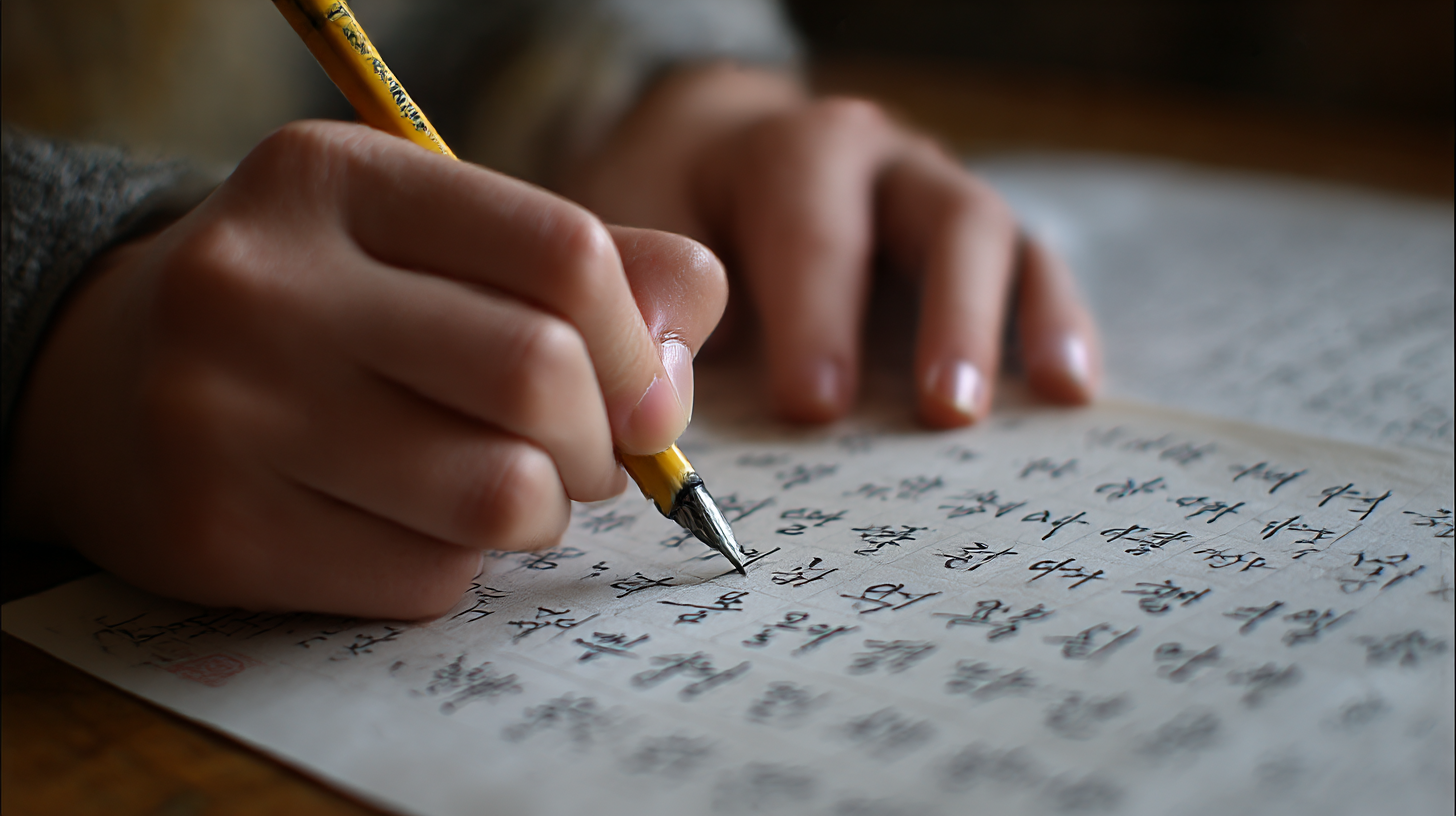
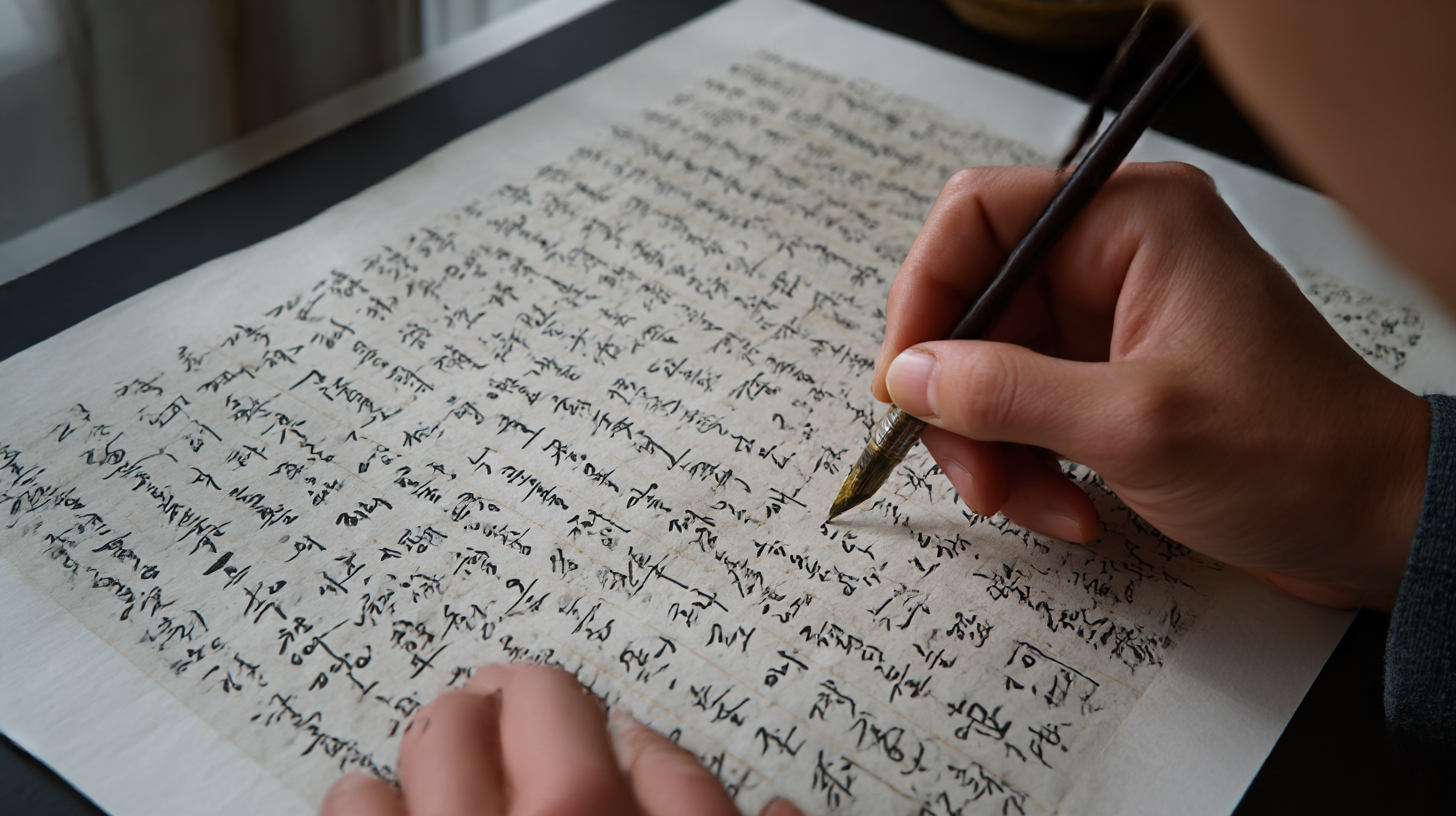
회사에서 인정받는 바른글씨 작성 비법 직장에서는 외모보다 글씨가 먼저 인상을 남길 때가 많아요. 회의자료, 메모, 업무 노트에서 글씨는 곧 나를 대표하는 얼굴이 되기도 해요. 글씨 하나 바뀌었을 뿐인데 “성실하다”, “정리정돈 잘한다”는 칭찬을 들은 분들도 정말 많답니다.
그렇다면 어떻게 하면 회사에서 칭찬받는 ‘바른 글씨’를 쓸 수 있을까요? 특별한 재능이 없어도 누구나 실천 가능한 방법들을 지금부터 알아볼게요. 내가 생각했을 때 글씨는 습관이에요. 매일 조금씩 바르게 쓰려고 노력하면 얼마든지 멋진 글씨체가 내 것이 된답니다! 😊
✏ 글씨체가 주는 첫인상의 힘
직장에서 글씨는 당신의 이미지를 형성하는 데 큰 역할을 해요. 예쁘게 정돈된 글씨는 신뢰감, 성실함, 집중력 있는 사람으로 보이게 만들죠. 반면, 지저분한 글씨는 일의 완성도까지 낮춰 보일 수 있어요. 상사나 동료가 여러분의 업무 메모나 회의 노트를 보는 순간, 글씨로 인상을 받는 경우가 많답니다.
특히 보고서나 회의록을 직접 손글씨로 작성할 경우, 글씨가 가지는 무게감은 더 커져요. 아무리 좋은 내용을 담고 있어도 읽기 어려운 글씨라면 전달력이 떨어지고 신뢰도까지 깎일 수 있죠. 실제로 많은 회사에서는 직원의 글씨체를 평가 기준의 하나로 삼기도 해요.
또한, 깔끔하고 일정한 글씨는 본인의 사고 방식까지 잘 정돈되어 있다는 느낌을 주기 때문에 업무 능력까지 높게 평가받을 수 있어요. 이런 이유로 ‘글씨 하나 잘 써서 승진했다’는 이야기까지 있을 정도예요.
직장인에게 글씨는 단순한 표현 수단이 아니에요. 명함처럼 자신의 이미지를 보여주는 도구예요. 그렇기 때문에 지금부터라도 조금씩 바른 글씨 연습을 시작하면 업무 능력과 함께 이미지까지 동시에 좋아질 수 있어요.✌
📝 글씨체별 인상 비교표
글씨 유형 주는 인상 추천 상황 둥글고 단정한 글씨 부드럽고 친근함 회의 메모, 피드백 획이 굵고 또렷한 글씨 결단력 있고 정확함 보고서, 기획서 기울어진 글씨 창의적이고 감성적 아이디어 회의, 제안서 작고 정돈된 글씨 섬세하고 논리적 업무 노트, 체크리스트 각 글씨체는 상황에 따라 더 효과적으로 쓰일 수 있어요. 따라서 자신만의 스타일을 만드는 것도 중요하지만, 상황에 맞게 글씨 분위기를 조절하는 능력도 실무에선 매우 유용하답니다!
📐 바른글씨를 위한 기본 원칙
바른글씨를 쓰기 위해서는 단순히 예쁘게만 쓰려고 하지 말고, 기본 원칙을 지키는 것이 훨씬 중요해요. 기본적인 획과 자형, 자간, 행간만 잘 맞춰줘도 깔끔한 인상을 줄 수 있답니다. 글씨 연습을 시작할 때 가장 먼저 해야 할 건 글자의 구조를 이해하는 거예요.
예를 들어, 모든 자음과 모음은 일정한 기준선을 따라 쓰는 것이 중요해요. 초성은 왼쪽, 중성은 가운데, 종성은 아래쪽에 정렬하는 원칙만 지켜도 전체적으로 안정감 있는 글씨가 돼요. 한 글자 안에서 중심축을 일정하게 유지하면 전체 문장이 흐트러지지 않아요.
자간은 너무 좁지도 넓지도 않게 일정하게 유지해야 해요. 너무 좁으면 답답해 보이고, 너무 넓으면 흐트러진 느낌이 나요. 한글은 정사각형 틀 안에 글자를 맞춰 쓰는 것이 기본이라서, 가상의 정사각형 안에 각 글자가 정확히 들어간다는 느낌으로 연습해 보세요.
글씨를 바르게 쓰려면 속도 조절도 중요해요. 급하게 쓰면 글자의 균형이 무너지고 획이 휘어지기 쉬워요. 일정한 속도로 천천히 써 내려가면 손의 움직임도 안정되고 글씨가 훨씬 고르게 보이게 돼요. 급한 메모를 할 때도 의식적으로 균형을 생각해보면 훨씬 나아져요.
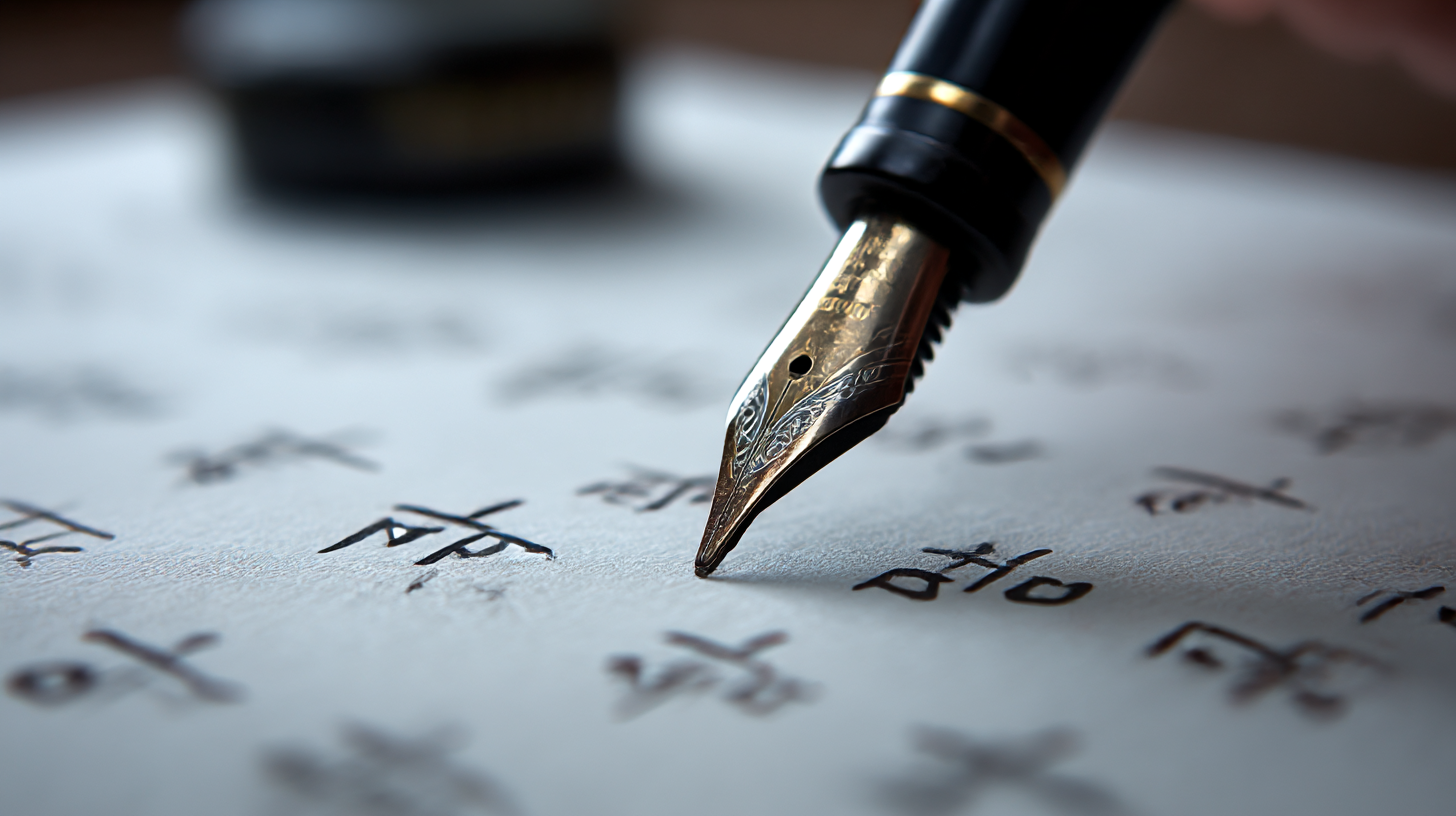
바른글씨를 위한 기본 원칙 📏 바른글씨 원칙 요약표
항목 설명 주의사항 자형 정렬 가상의 정사각형 안에 글자 균형 맞추기 중심선 무너지지 않도록 자간 유지 글자 간 일정한 간격 유지 너무 붙거나 멀어지지 않게 획의 균형 가로·세로 획의 두께와 길이 일정하게 한 쪽으로 쏠리지 않게 속도 조절 급하게 쓰지 말고 일정한 리듬 유지 빨리 쓰면 글씨가 휘어짐 기본을 지키는 것이 곧 실력이에요. 특별한 장식 없이도 바르고 단정한 글씨는 직장 내에서 가장 큰 무기가 될 수 있답니다. 기본기부터 다시 다져보면, 누구든 멋진 글씨체를 가질 수 있어요! 💪
🖋 글씨 연습 루틴 만들기
바른 글씨를 위해선 규칙적인 연습이 가장 중요해요. 하루 10분만 투자해도 한 달 후에는 놀라운 변화를 느낄 수 있어요. 꾸준함은 실력을 만들고, 실력은 곧 자신감이 되죠. 글씨 연습도 마찬가지예요. 처음부터 멋진 글씨를 쓸 수는 없지만, 올바른 루틴을 통해 분명히 발전할 수 있어요.
가장 먼저 해야 할 것은 ‘기본 획 연습’이에요. 세로획, 가로획, 점, 꺾임 등을 규칙적으로 반복하면서 손에 익히는 것이 핵심이에요. 한글은 특히 ‘ㅅ’, ‘ㅈ’, ‘ㅂ’처럼 꺾임이 많은 글자가 많기 때문에 획 연습은 필수예요. 기본 획이 안정되면 자연스럽게 자형도 안정돼요.
그다음에는 자주 쓰는 단어들을 중심으로 연습해보세요. “보고서”, “기획안”, “회의록” 같은 직장에서 자주 쓰는 단어들을 쓰는 연습을 하면 실전에서도 당황하지 않고 또박또박 쓸 수 있어요. 단어가 익숙해질수록 손도 편해지고, 글씨체도 자연스러워져요.
마지막으로는 문장 단위로 연습하는 걸 추천해요. 짧은 문장을 적어보면서 자간과 행간, 글줄 정렬까지 익혀보세요. 연습 문장으로는 책 속의 문장이나 명언 등을 활용하면 의미도 있고 흥미도 생기죠. 매일 한 문장이라도 쓰는 습관이 실력을 만들어줘요!
🗓 추천 글씨 연습 루틴표
요일 연습 내용 소요 시간 월요일 기본 획 연습 (세로/가로/점/꺾기) 10분 화요일 자형 중심 연습 (가상의 정사각형) 15분 수요일 실무 단어 쓰기 (회의, 업무명 등) 10분 목요일 속도 조절 및 일정한 필기 연습 10분 금요일 문장 연습 (명언/기사 등 필사) 15분 매일 정해진 시간에 같은 루틴을 반복하면 뇌가 자연스럽게 ‘글씨 쓰는 시간’으로 인식하게 돼요. 습관이 되면 손도 마음도 편안해져서 더 좋은 글씨를 쓸 수 있게 되죠. 누구나 멋진 글씨를 가질 수 있어요. 지금 당장 오늘부터 시작해봐요! 💫
🖊 도구 선택도 중요해요
글씨 연습에서 도구는 생각보다 정말 큰 영향을 줘요. 펜 하나 바꿨을 뿐인데 글씨 느낌이 달라지고, 손에 힘도 다르게 들어가거든요. 자신에게 잘 맞는 펜과 노트를 찾는 것은 마치 운동화 고르듯이 신중해야 해요. 손의 압력, 종이의 질감, 펜촉의 흐름까지 모두 글씨체에 영향을 줘요.
먼저 펜은 너무 미끄럽거나 끊기는 느낌이 없도록 부드럽게 써지는 것을 고르는 게 좋아요. 유성볼펜보다는 젤펜이나 수성펜이 글씨 연습용으로는 더 좋다는 평이 많아요. 특히 0.38mm~0.5mm 굵기의 젤펜은 획이 균일하게 나와서 자형을 잡기 쉬워요.
종이는 너무 미끄럽거나 너무 거친 표면은 피하는 게 좋아요. 매끄럽지만 살짝 텍스처가 있는 종이가 글씨 연습에는 적합하답니다. 유선 노트도 좋지만, 글씨체를 정돈하려면 모눈 노트나 10mm 간격의 가이드 노트도 적극 추천해요.
추가로, 바른 자세와 그립도 중요해요. 펜을 너무 꽉 쥐면 손에 피로가 오고 글씨도 흐트러지기 쉬워요. 손가락 끝이 펜촉에서 2cm 정도 떨어지게 잡고, 손목은 힘을 빼는 게 핵심이에요. 올바른 도구와 자세는 글씨 연습의 기초 체력을 길러주는 역할을 해요.💪
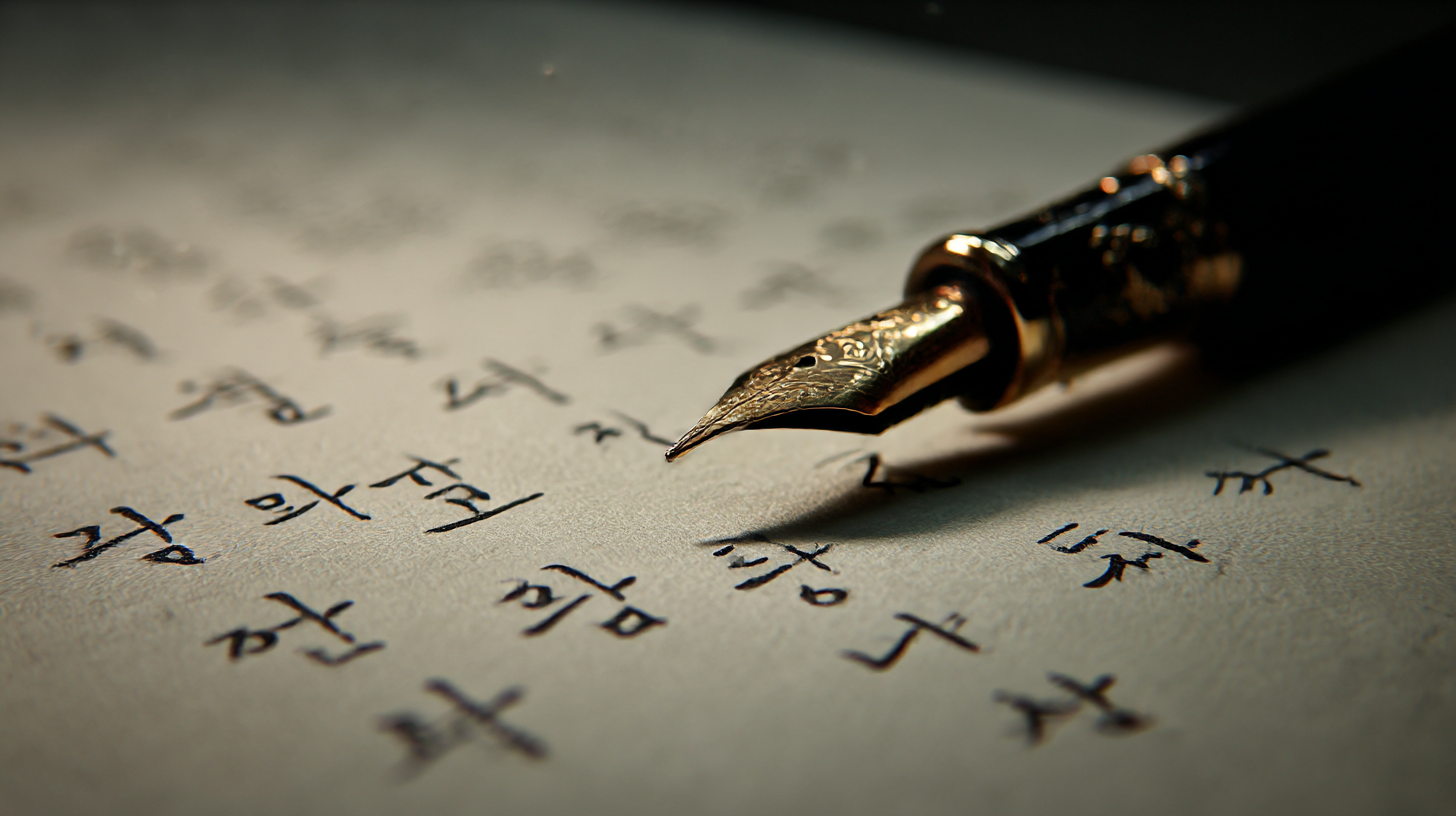
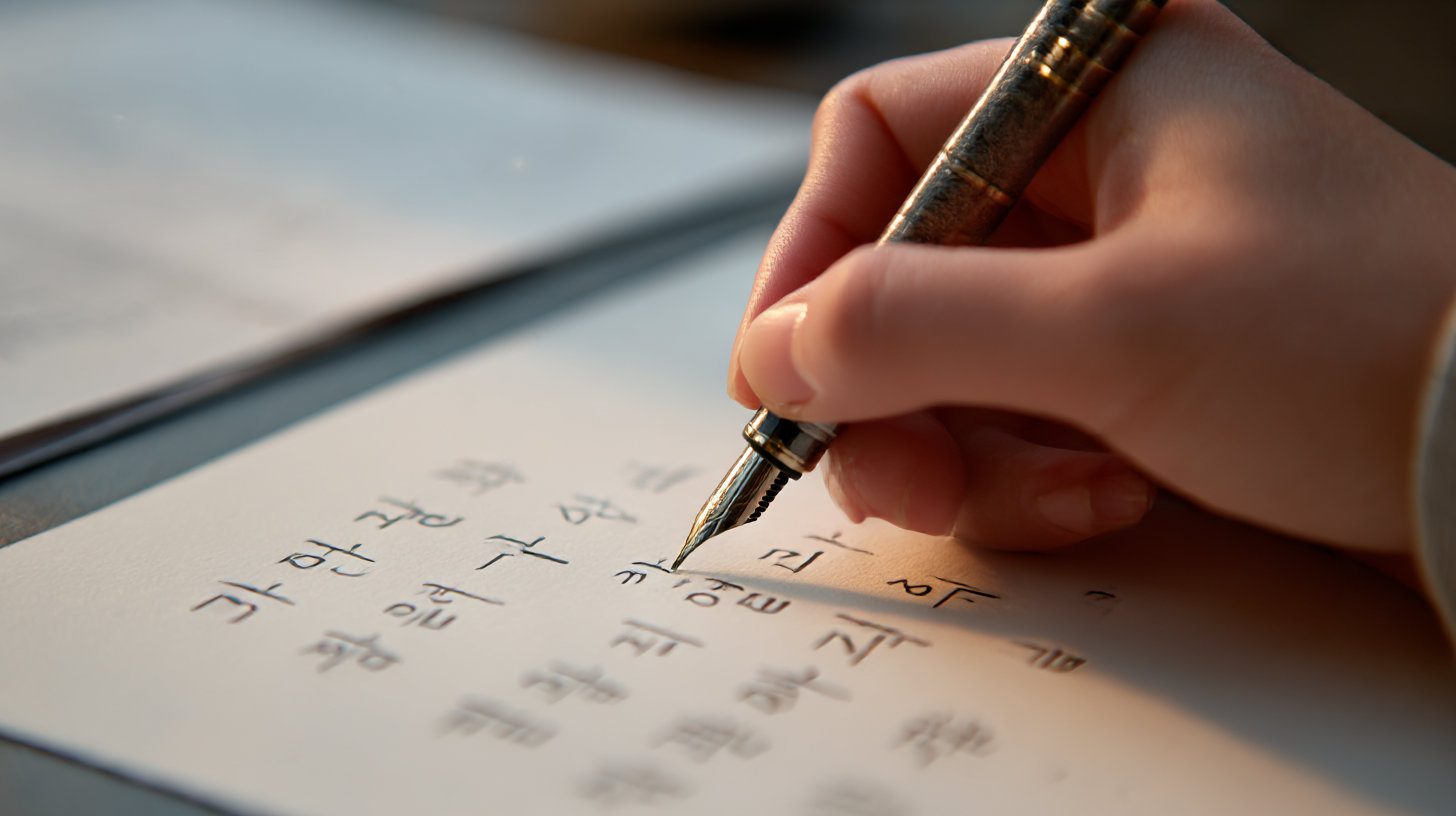
도구 선택도 중요해요 ✍ 추천 필기 도구 비교표
도구 특징 추천 사용자 젤펜 0.38mm 선이 얇고 섬세하게 나옴 초보자, 글자 균형 잡기 용이 수성펜 부드러운 필기감 중간 숙련자, 감성 글씨 연습 만년필 획의 두께 조절 가능 고급 필기체 연습용 모눈 노트 자간·자형 연습에 적합 글씨체 교정 단계에 추천 글씨 연습의 성공은 도구 선택에서 시작돼요. 손에 맞는 펜을 찾고, 내가 좋아하는 노트에 글씨를 써보는 것만으로도 글씨체는 점점 안정돼요. 자신에게 가장 잘 맞는 도구를 찾는 것부터 시작해보세요! 🎯
📄 회사에서 통하는 글씨 습관
회사에서 칭찬받는 글씨는 단순히 예쁘기만 한 게 아니에요. 명확하게 읽히고, 실용적으로 구성돼야 해요. 바로 그런 글씨가 ‘실무형 바른 글씨’랍니다. 이 실무형 글씨를 쓰기 위해선 몇 가지 글쓰기 습관을 갖는 게 정말 중요해요. 습관 하나만 바꿔도 인상이 확 달라진답니다.
먼저, 문서나 메모를 작성할 때 일정한 글자 크기를 유지하는 것이 좋아요. 글씨 크기가 들쭉날쭉하면 가독성이 떨어지고 상대방이 읽기 불편하거든요. 특히 회의 중 작성하는 노트나 피드백 메모일수록 글자 크기를 신경 써야 해요.
또한, 중요한 단어나 항목은 여백을 활용해 강조하면 좋아요. 형광펜이나 밑줄을 사용하는 대신, 글씨만으로 포인트를 주고 싶다면 글자를 약간 굵게 쓰거나, 정자체를 사용하는 게 효과적이에요. 형식적인 표현보단 실용적인 글씨 배치가 업무에서는 훨씬 신뢰를 얻어요.
그리고 메모나 회의록 작성 시, 줄을 맞추는 습관도 매우 중요해요. 줄 간격과 문단 정렬이 깔끔하면 보고하는 자료로도 손색이 없거든요. 메모장에 글을 작성할 때도 항상 좌우 여백을 신경 쓰면서 쓰는 습관을 들이면 자연스럽게 정돈된 인상을 줄 수 있어요.👌
📘 실무형 글씨 습관 비교표
좋은 습관 효과 적용 상황 글자 크기 일정하게 유지 가독성 향상, 안정된 인상 회의 노트, 메모장 여백 활용한 강조 내용 전달력 향상 업무 피드백, 요약 정리 줄 맞춤 & 정렬 전문적이고 깔끔한 인상 보고서, 회의록 줄 간격 일정 유지 읽는 이의 집중력 증가 수첩, 필기 노트 직장에서는 ‘보기 좋은 글씨’가 아니라 ‘읽기 쉬운 글씨’가 칭찬받는 법이에요. 실무에서 바로 사용할 수 있는 글씨 습관을 꾸준히 연습해두면, 어느 순간 동료들이 “글씨 너무 잘 쓰시네요”라고 말해줄 거예요! 😄
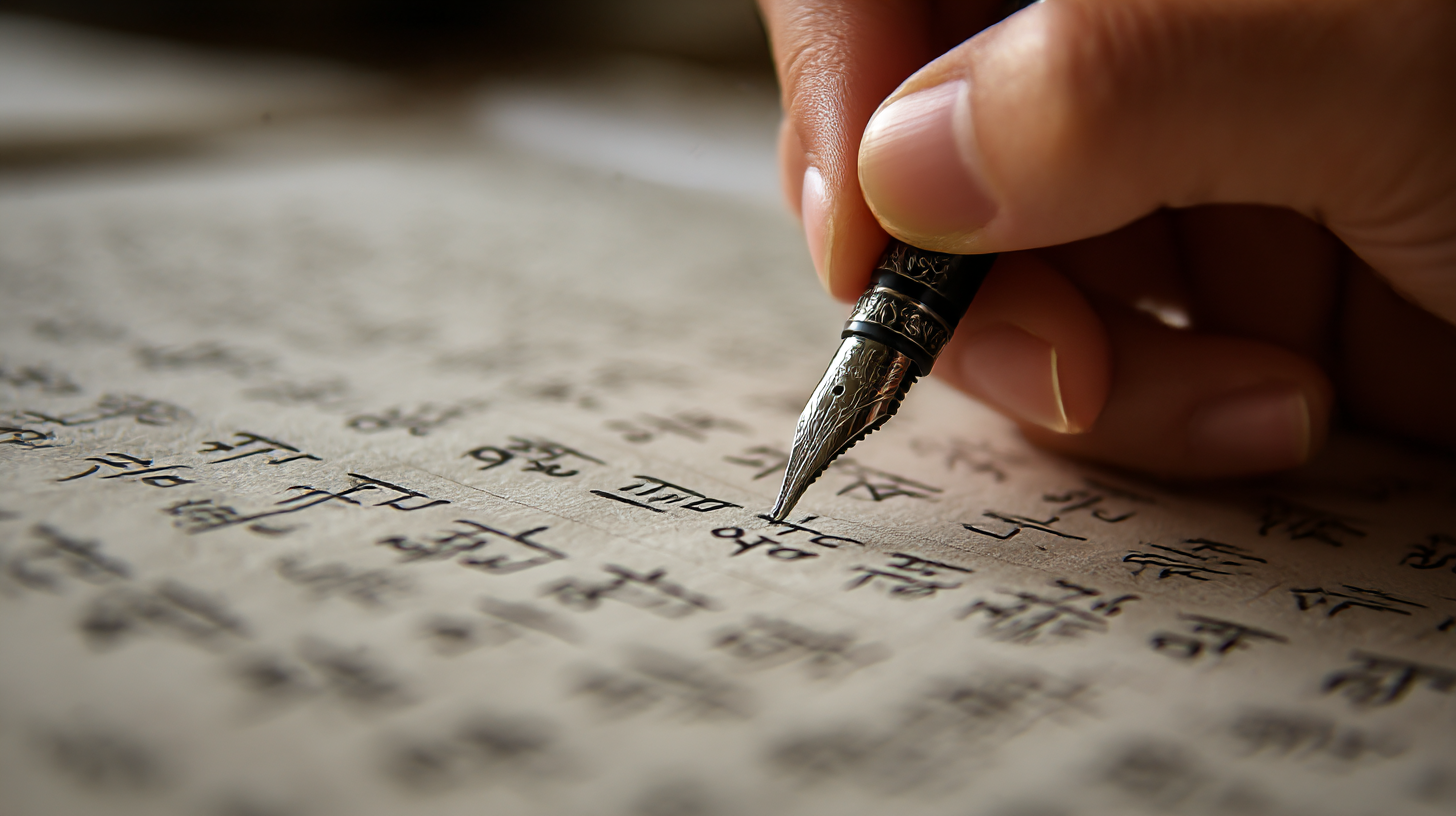
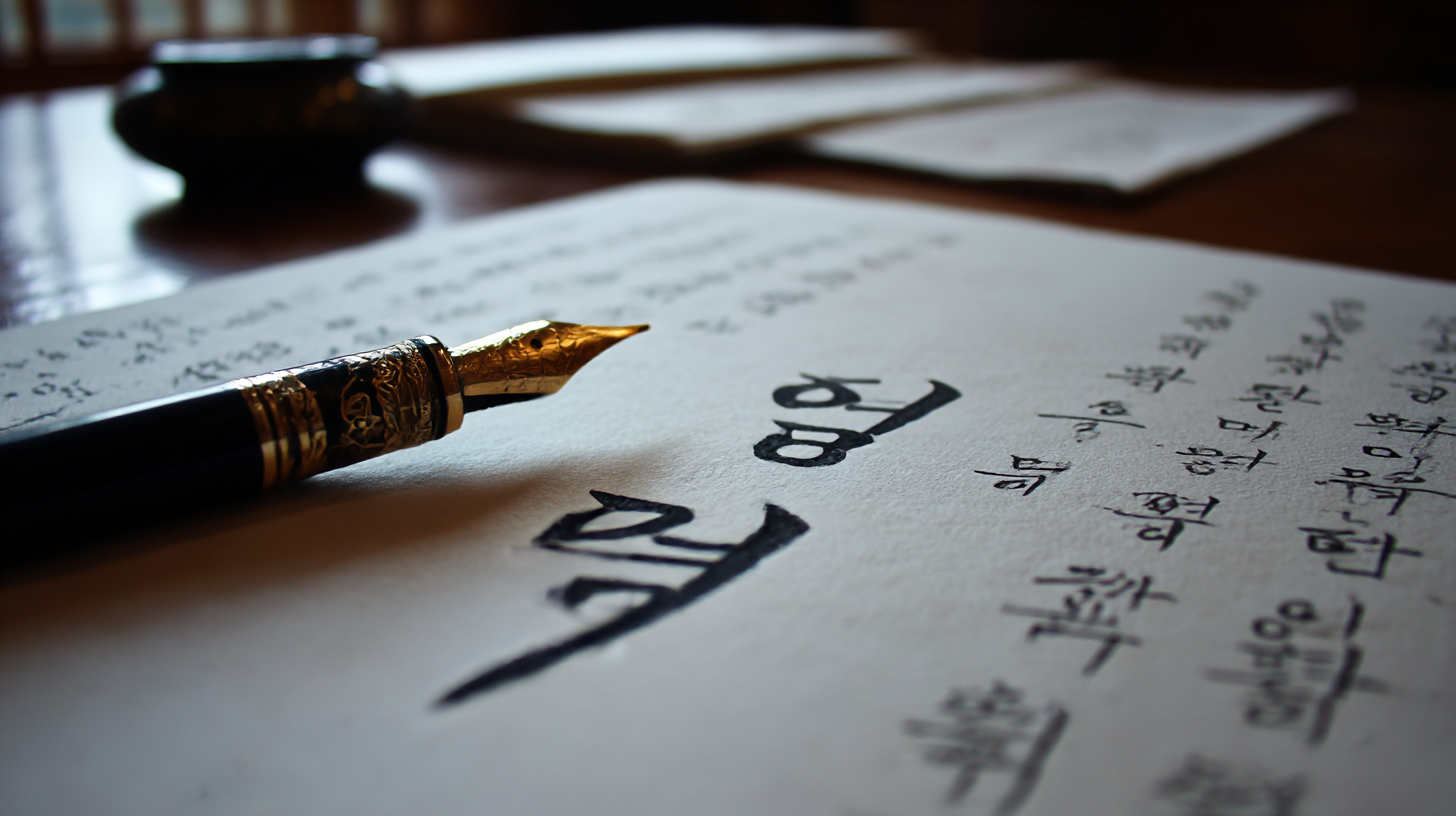
회사에서 통하는 글씨 습관 🧠 글씨체가 성격까지 보여줄까?
우리가 무심코 쓰는 글씨에도 성격과 기질이 드러난다고 해요. 실제로 심리학에서는 글씨체를 분석해 성향을 파악하는 '그래포로지(graphology)'라는 분야도 존재해요. 물론 과학적인 진단은 아니지만, 글씨에서 느껴지는 분위기나 정돈 상태를 보면 그 사람의 성향을 어느 정도 유추할 수 있어요.
Q4. 펜 추천해줄 수 있나요?
A4. 0.38mm 젤펜(하이테크C, 유니볼 시그노)이나 수성펜(플래티넘 프레피) 추천드려요. 필기감도 좋고 초보자에게도 딱이에요.
Q5. 글씨체 교정을 독학으로 해도 괜찮을까요?
A5. 네! 요즘은 유튜브나 필사노트, 연습장도 많아서 혼자서도 충분히 가능해요. 꾸준한 연습만이 정답이에요.
Q6. 글씨체 하나로 성격까지 판단될 수 있나요?
A6. 완전히 판단할 순 없지만, 글씨에서 느껴지는 분위기나 인상은 분명히 성격의 일부를 반영하기도 해요.
Q7. 글씨 연습 시간을 언제 정하는 게 좋을까요?
A7. 아침 출근 전 10분, 점심시간 후 여유시간, 잠들기 전 등이 좋아요. 반복성이 중요해서 하루 한 번이라도 정해두는 게 좋아요.
Q8. 회사에서 글씨 잘 쓰면 진짜로 칭찬을 받을까요?
A8. 네! 특히 상사나 동료가 여러분의 메모나 회의록을 읽을 때 깔끔하고 또박또박한 글씨는 업무 스타일까지 긍정적으로 보여줘요.